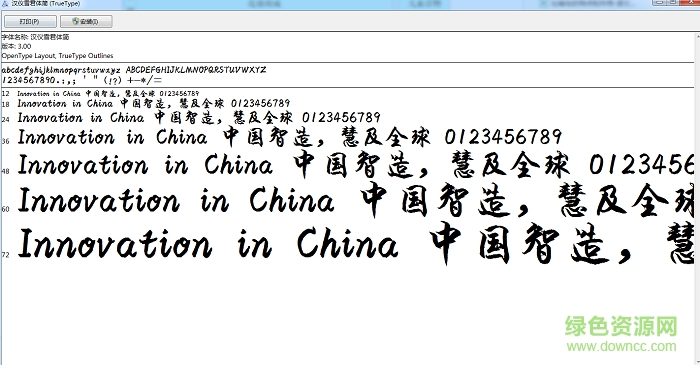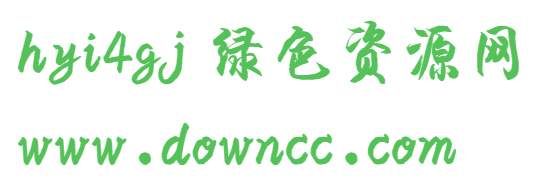
hyi4gj(汉仪雪君体简)
hyi4gj是什么字体?hyi4gj字体又叫汉仪雪君体简,笔画相叠,线条勾勒恰当,精致漂亮,需要这款字体的朋友快来绿色资源网下载这款艺术字体吧!
hyi4gj字体特点
汉仪雪君体简每个字顶上如白雪覆盖,高低错落,似山顶上的雪峰,可以广泛应用于广告设计、宣传海报、PPT、影视制作以及任何使用文字的领域。
hyi4gj 汉仪雪君体简